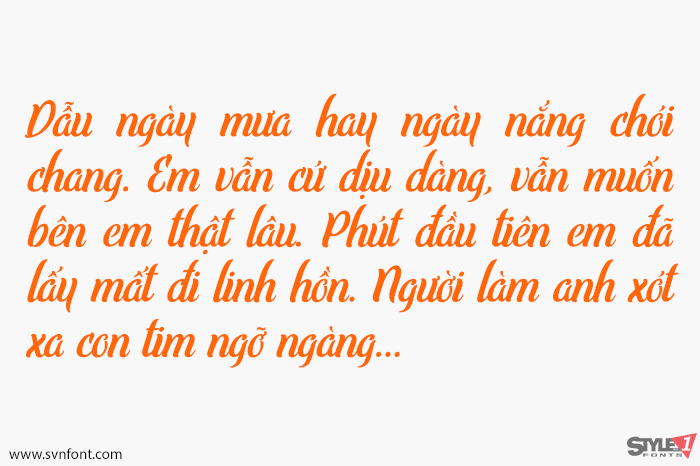
Elley được tạo ra nhằm giúp bạn dễ dàng hơn trong việc thực hiện các công việc typography như thiết kế logotype, poster, tiêu đề, áo thun và nhiều dự án sáng tạo khác.
Nhà thiết kế: Typesgal
Nhà phát hành: Typesgal